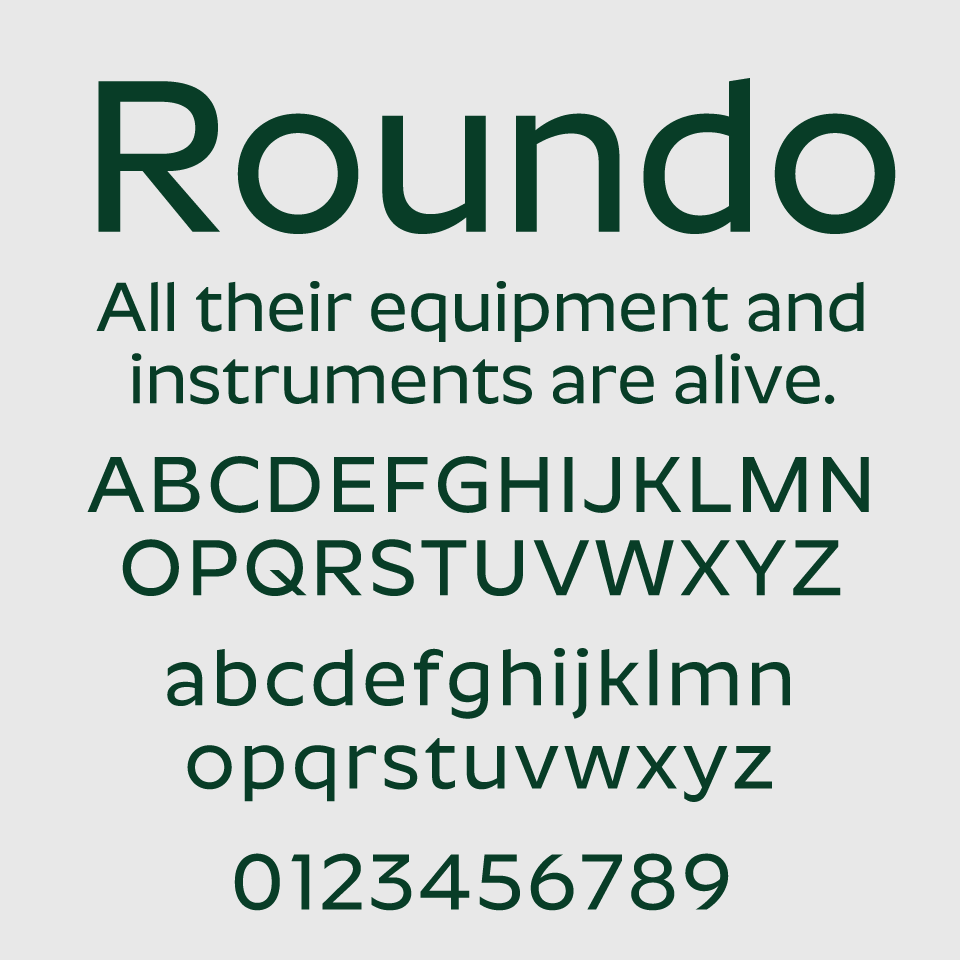
Roundoフォントは、その名の通り角の取れた丸みのあるシルエットが特徴のサンセリフ体です。文字全体にやさしさと温かみがあり、どこか親しみを感じさせる雰囲気を持っています。クリーンで整った形状なので、読みやすさも抜群です。
印象としては、穏やかで信頼感のあるトーンを表現したいときに最適です。保育・教育・ライフスタイル系のグラフィック、あるいは温かみのあるブランドのロゴなどにも活用しやすいフォントです。